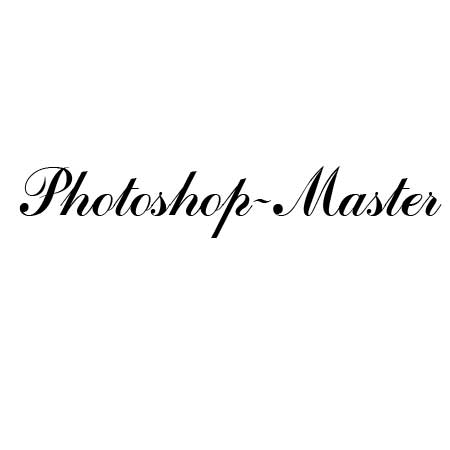
Дополнения Шрифты Татьяна Гапонова 21 февраля 2009 Шрифт - OdessaScriptFWF Regular Красивый шрифт без поддержки русского языка. Скачать Шрифт - OdessaScriptFWF Regular